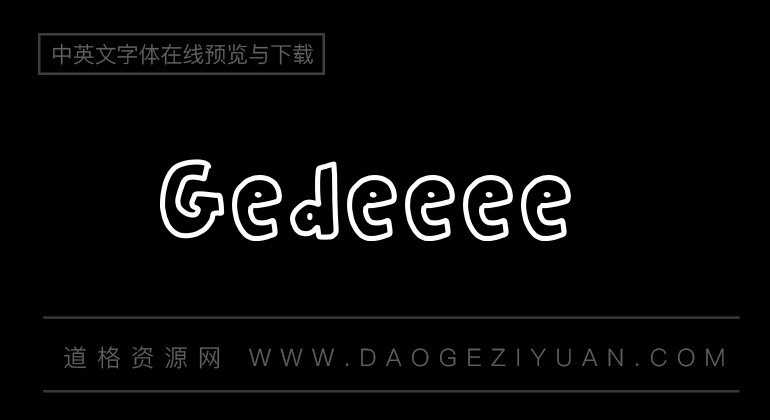
Gedeeee 是一款由西班牙设计师 Eduardo Tunni 创作的手写风格字体。这款字体具有独特的手写形状,细节丰富,笔画清晰,整体看起来更加自然,更有趣。它具有温暖、轻松、活泼的特色,适合用于商业广告、海报、标识和卡通等设计中。内容介绍
Gedeeee 是一款非常不错的手写艺术字体,具有很好的视觉感,适合于文化类的宣传设计、商业类品牌的广告和产品包装设计以及个性化文字排版等较多场景。